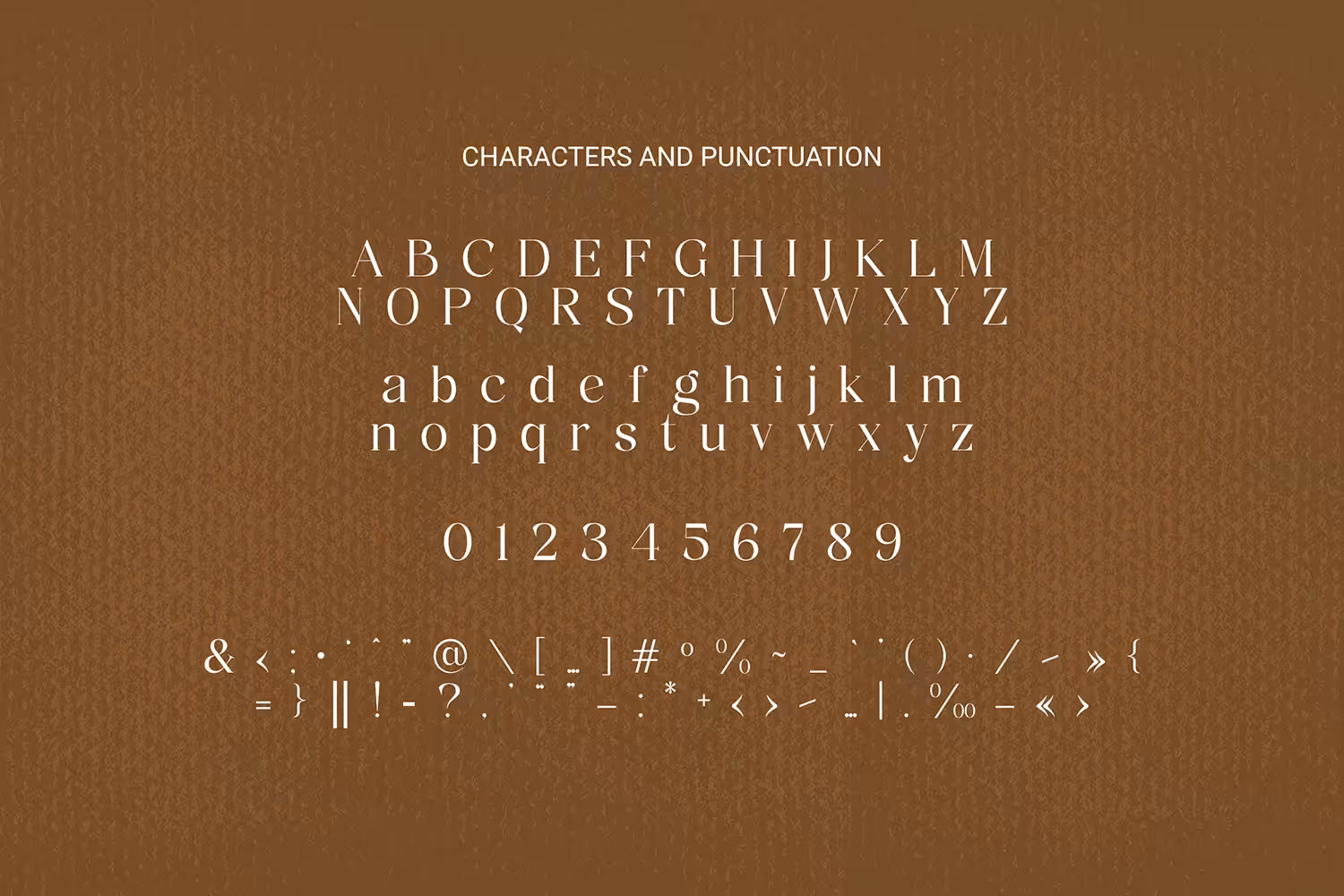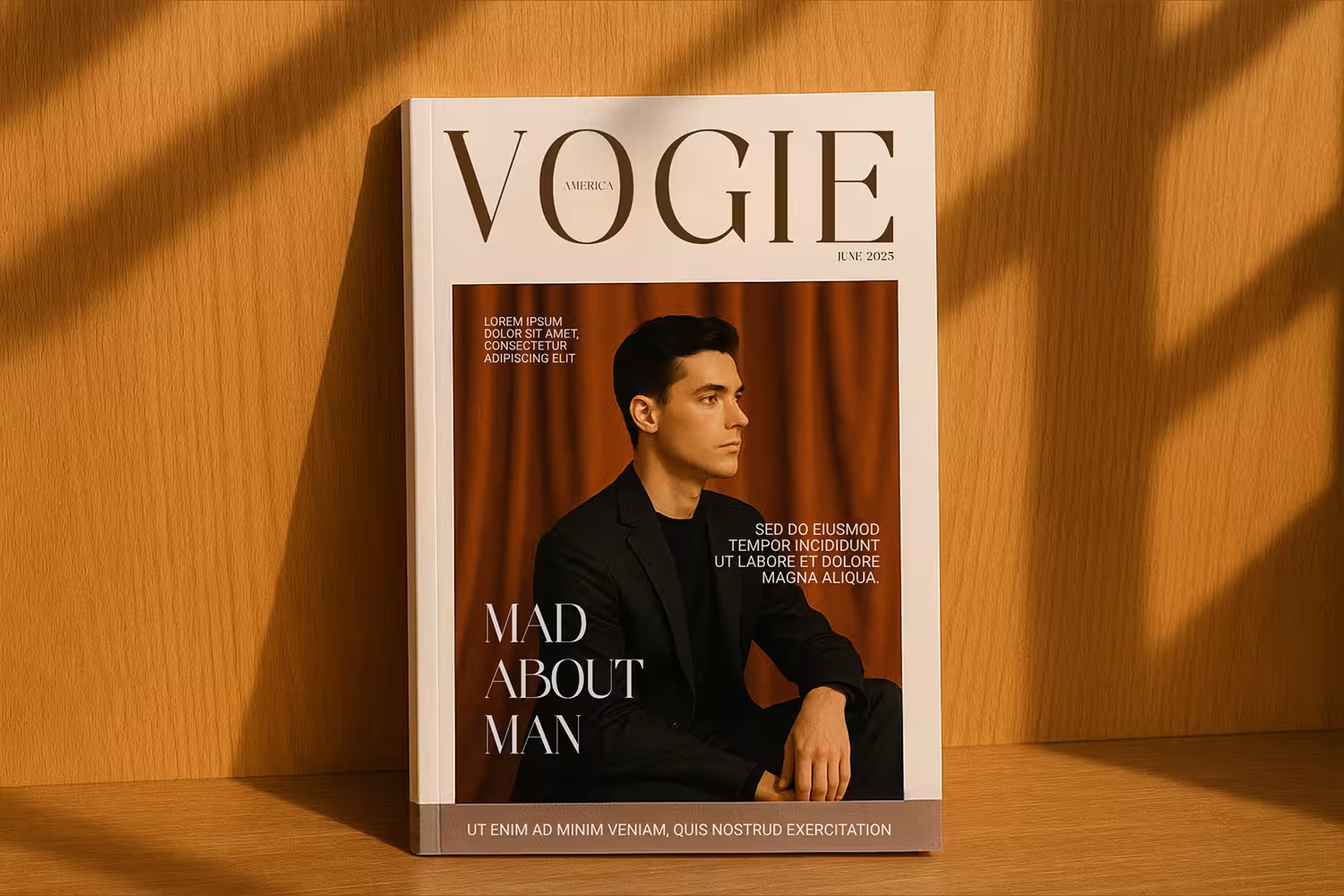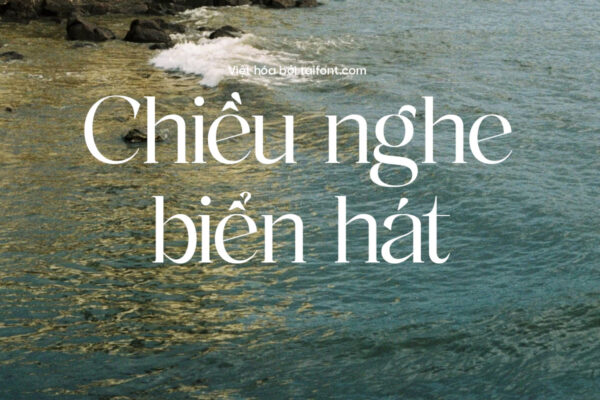
Giới thiệu về Font TF Amorenchia Việt hóa
TF Amorenchia Việt hóa là một font chữ có chân (serif) nổi bật với thiết kế mạnh mẽ, dứt khoát và đầy ấn tượng. Font này mang đến vẻ ngoài sang trọng, uy quyền và đầy cuốn hút, toát lên phong thái chuyên nghiệp và đẳng cấp, lý tưởng cho mọi ấn phẩm cần sự tinh xảo và độc đáo.
Với sự mạnh mẽ trong từng ký tự và tính thẩm mỹ vượt trội, Amorenchia là lựa chọn hoàn hảo cho các thiết kế muốn truyền tải sự sang trọng và phong cách, đặc biệt là trong các lĩnh vực:
- Thiết kế thời trang: Hoàn hảo cho các thương hiệu thời trang cao cấp, từ logo, nhãn mác sản phẩm, đến các lookbook và chiến dịch quảng bá bộ sưu tập. Font này giúp truyền tải vẻ đẹp thanh lịch, đẳng cấp và độc đáo của trang phục, nâng tầm giá trị thương hiệu.
- Tạp chí thời trang: Lý tưởng để sử dụng cho các tiêu đề chính, lời dẫn, hoặc nội dung bài viết trong các tạp chí về thời trang, làm đẹp, lối sống cao cấp. Nét chữ có chân mạnh mẽ của Amorenchia giúp tăng tính trang trọng và dễ đọc, đồng thời tạo cảm giác cao cấp, thu hút độc giả.
- Thiết kế nhận diện thương hiệu: Phù hợp cho logo, tagline hoặc bộ nhận diện thương hiệu của các công ty, doanh nghiệp muốn truyền tải sự tinh tế, uy tín và sự thanh lịch. Amorenchia giúp xây dựng một hình ảnh thương hiệu vững chắc và dễ nhận diện.
- In ấn cao cấp: Đảm bảo khả năng đọc tốt trên giấy và tạo ấn tượng mạnh mẽ cho các ấn phẩm như brochure, catalogue, bao bì sản phẩm cao cấp, hoặc danh thiếp.
Với TF Amorenchia Việt hóa, bạn có thể dễ dàng thổi hồn tinh tế, sang trọng và vẻ đẹp hoàn hảo vào các thiết kế, tạo ra những sản phẩm không chỉ đẹp mắt mà còn đầy cảm xúc và sức hút đặc biệt.